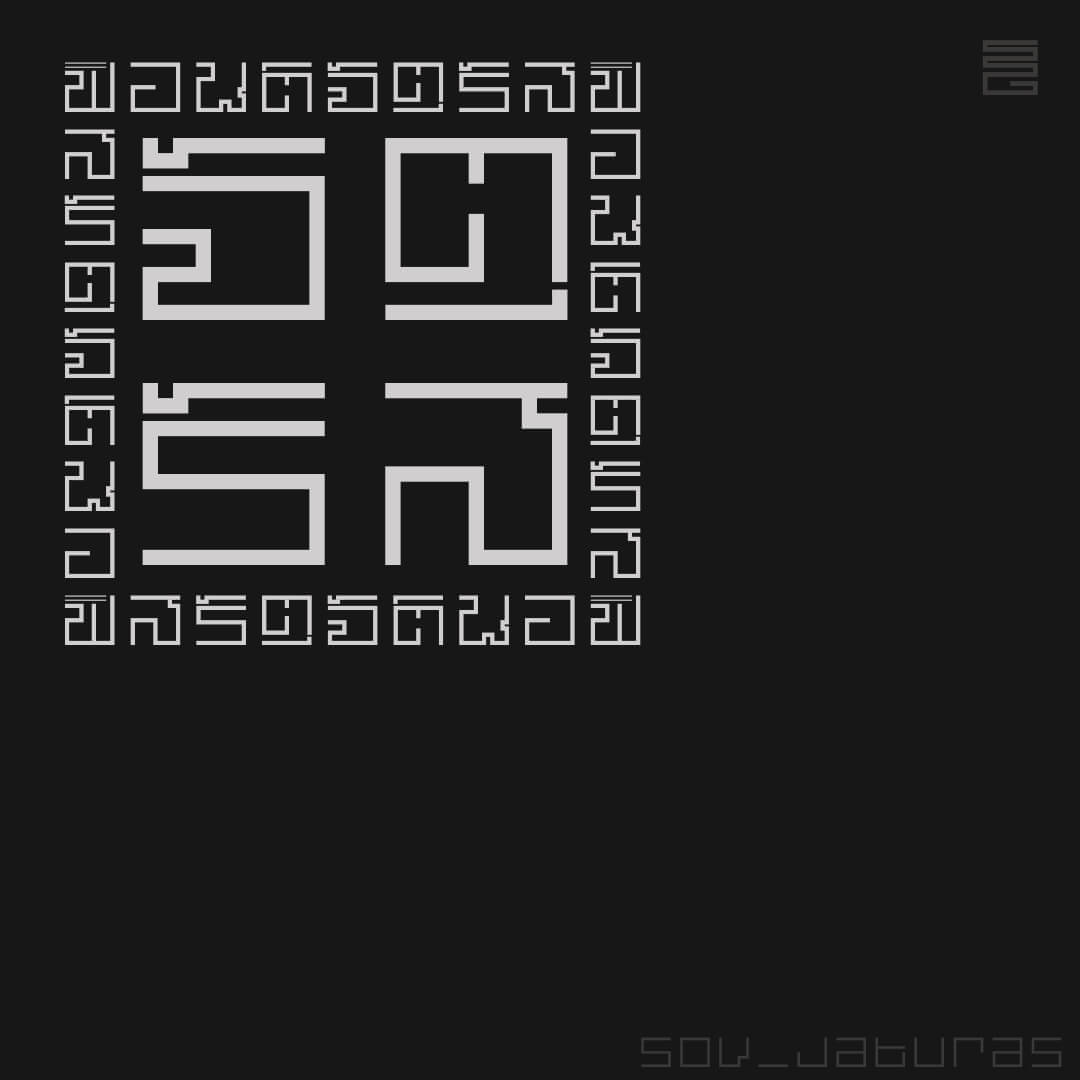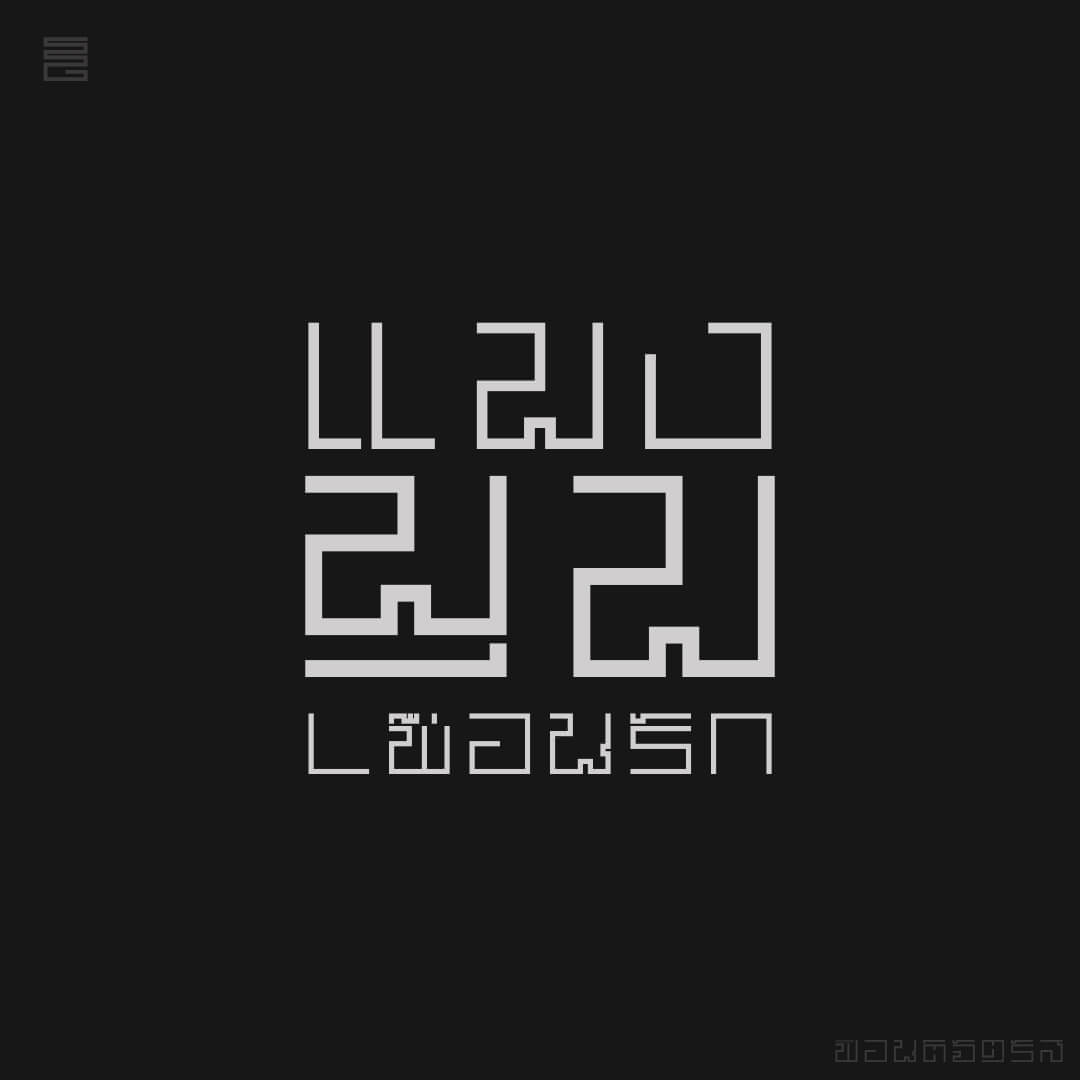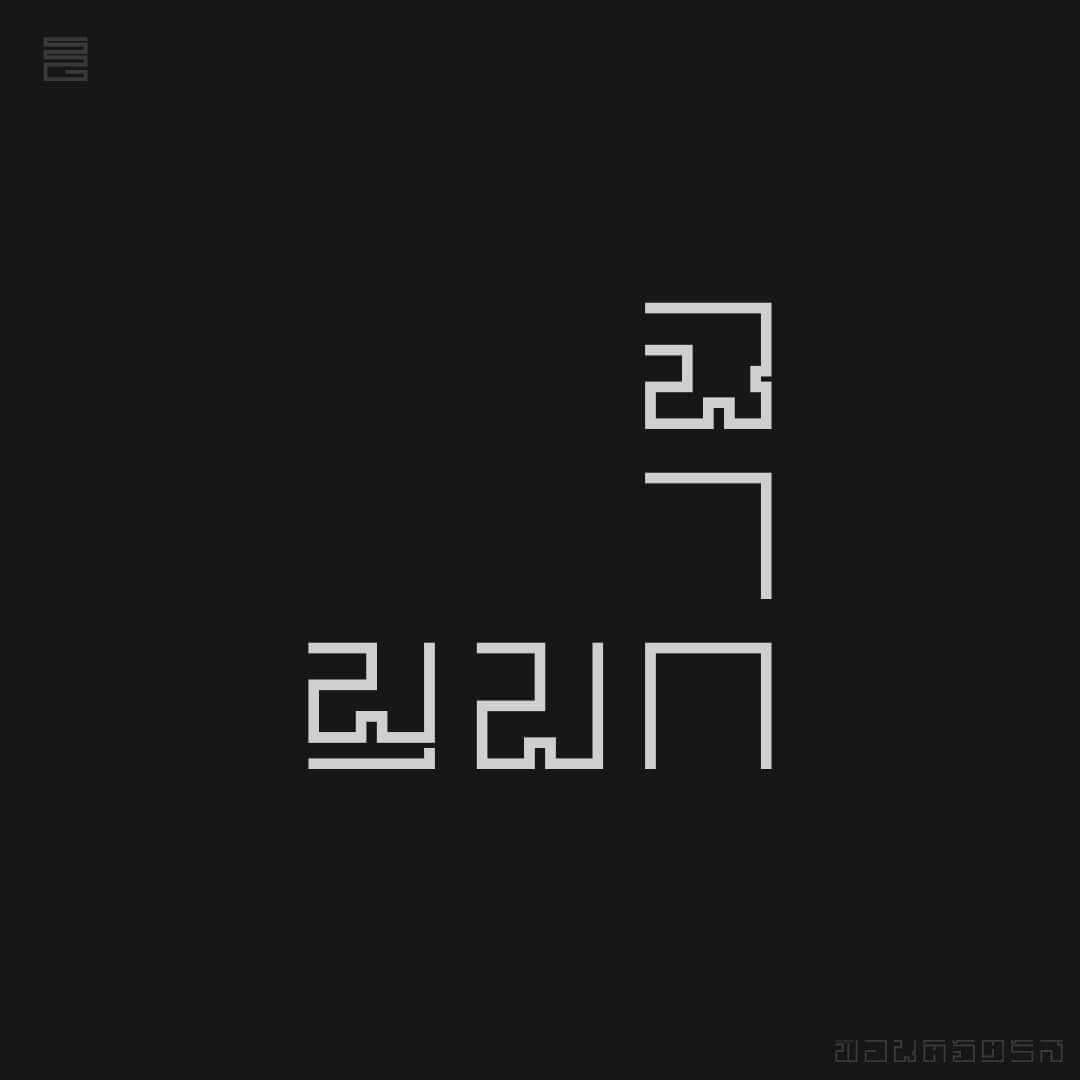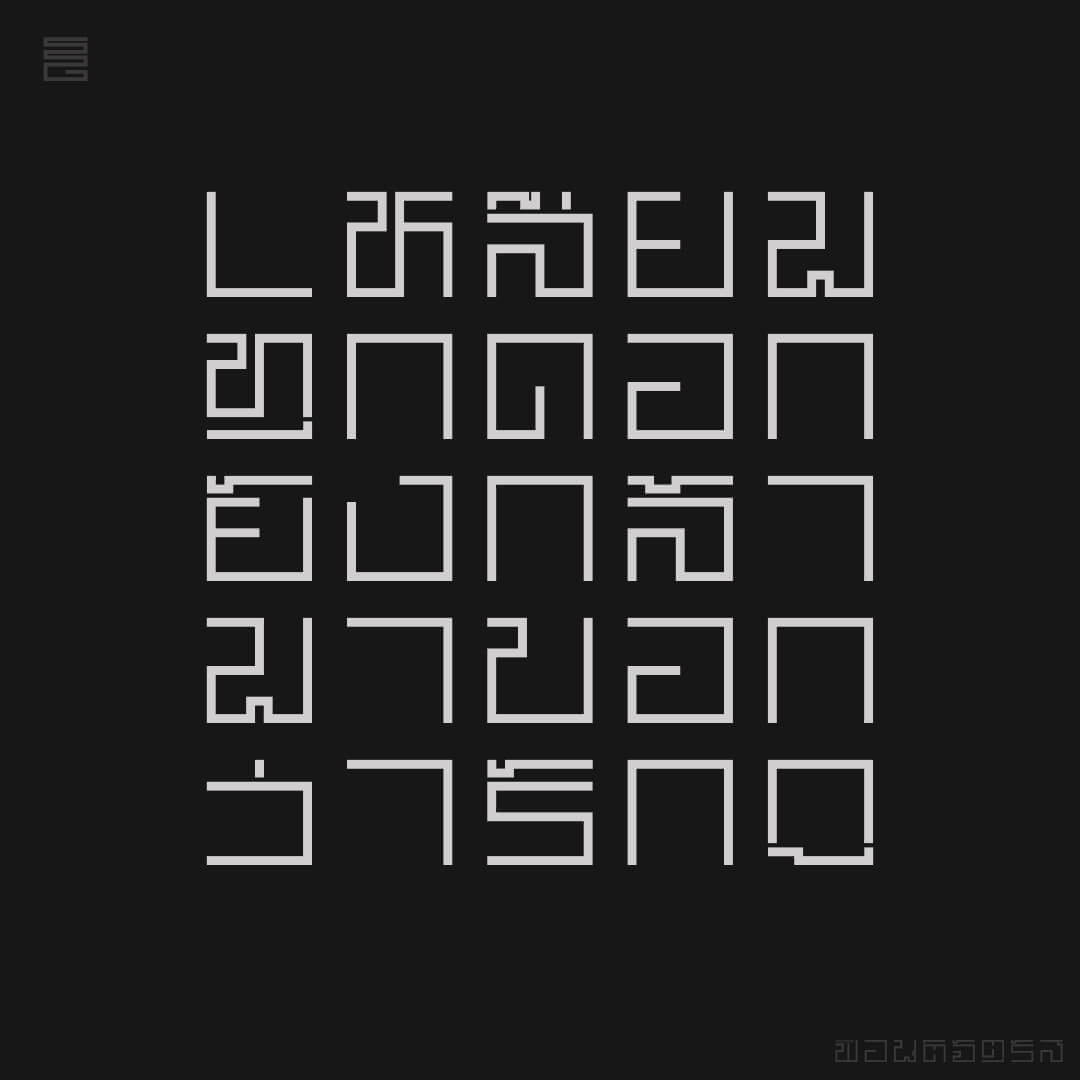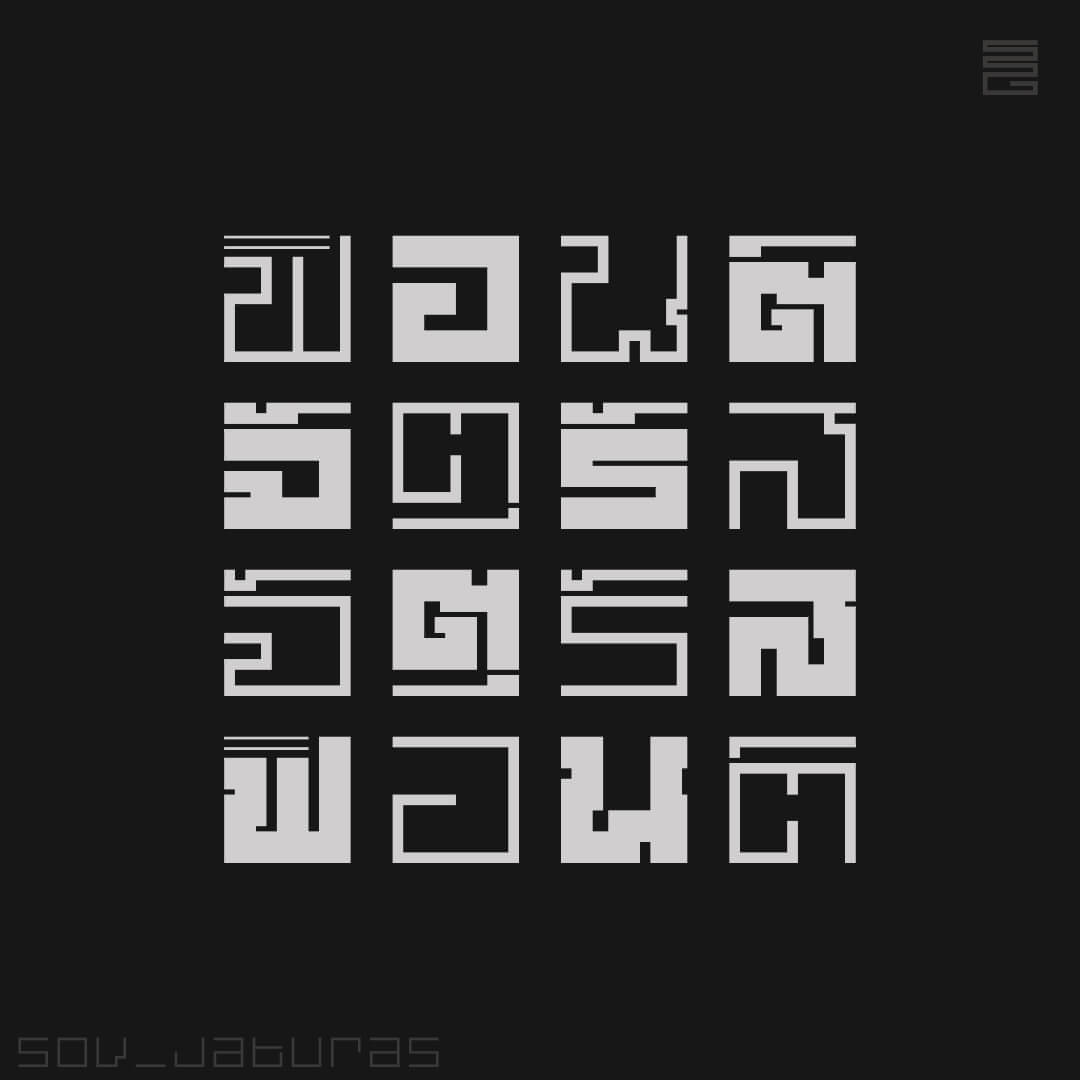
จัตุรัส (SOV_Jaturas)
ฟอนต์จัตุรัส – พยายามเป็นรูปสี่เหลี่ยมจัตุรัส ไม่ว่าจะมีวรรณยุกต์หรือไม่ ออกแบบมาใช้เป็น logo หรือจะใช้เป็นเม็ด pixel เอาไว้ต่อประกอบกันก็ได้
ถ้าจะใช้เป็นพาดหัว หรือข้อความ… ก็เพื่อเอามัน แต่อย่าเอาเรื่อง… เพราะอ่านไม่รู้เรื่อง (แต่ก็ยังจะทำตัวหนาเอาไว้ให้ใช้ เป็นความหนาเข้าด้านใน ขนาดเท่าตัวบาง 100%)
เบื้องหลังการออกแบบ : ฟอนต์ จัตุร้ส